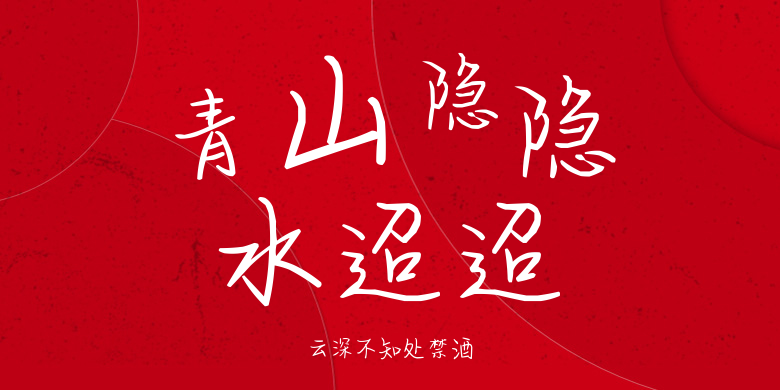
云深不知处禁酒
云深不知处禁酒,这款字体结构工整、笔画清晰,兼顾美观与易读性,适用于标题、正文、海报、包装、LOGO 等多种场景。字形优雅稳定,风格百搭耐看,适配日常排版与创意设计,让文字呈现更舒适、更具质感。云深不知处禁酒一笔一画,皆是细节,以均衡的比例、流畅的线条打造舒适视觉体验,字形端正大气,风格简约现代。无论是商业设计、品牌宣传还是日常排版,都能轻松驾驭,让文字更有格调与力量。云深不知处禁酒字体下载。